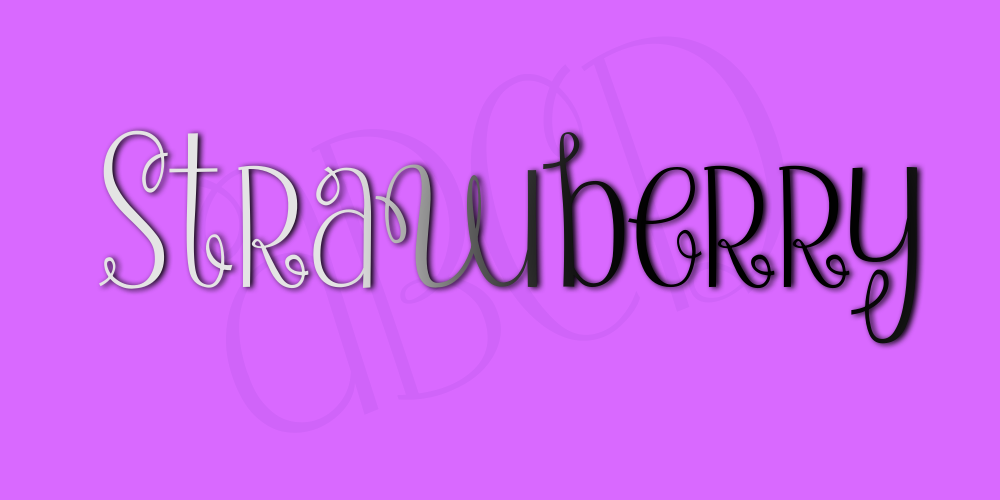
Strawberry Whipped Cream font – Download Grátis
A fonte “Strawberry Whipped Cream” é uma elegante escolha para aqueles que buscam adicionar um toque de luxo a suas criações digitais. Cada caractere desta fonte Blackletter exibe sua delicadeza e sofisticação, como se fossem fatias de doce creme de baunilha sobre o suco de morango fresquinho. Hamilton, o designer, pinta seus caracteres com precisão e cuidado para criar uma experiência visual que é tanto um prazer quanto um ato de criação. Esta fonte não apenas oferece uma versão suave e encorpada do creme de baunilha, mas também inclui uma pitada adicional da fruta madura em cada letra. Os traços finos são como as gotas delicadas que caem de um copo de sorvete quente; enquanto os traços grossos remetem às fatias gordurosas e redondas de creme de baunilha. Para designers apaixonados por gráficos, esta font é uma delícia para o olho. Ela traz à tona a arte do design, transformando simples símbolos em obras que refletem a perfeição da culinária e do desenho. Seja você um designer de blogs de receitas, criador de conteúdo pessoal ou designer gráfico, “Strawberry Whipped Cream” pode ser uma paixão inconfundível para seu trabalho diário.